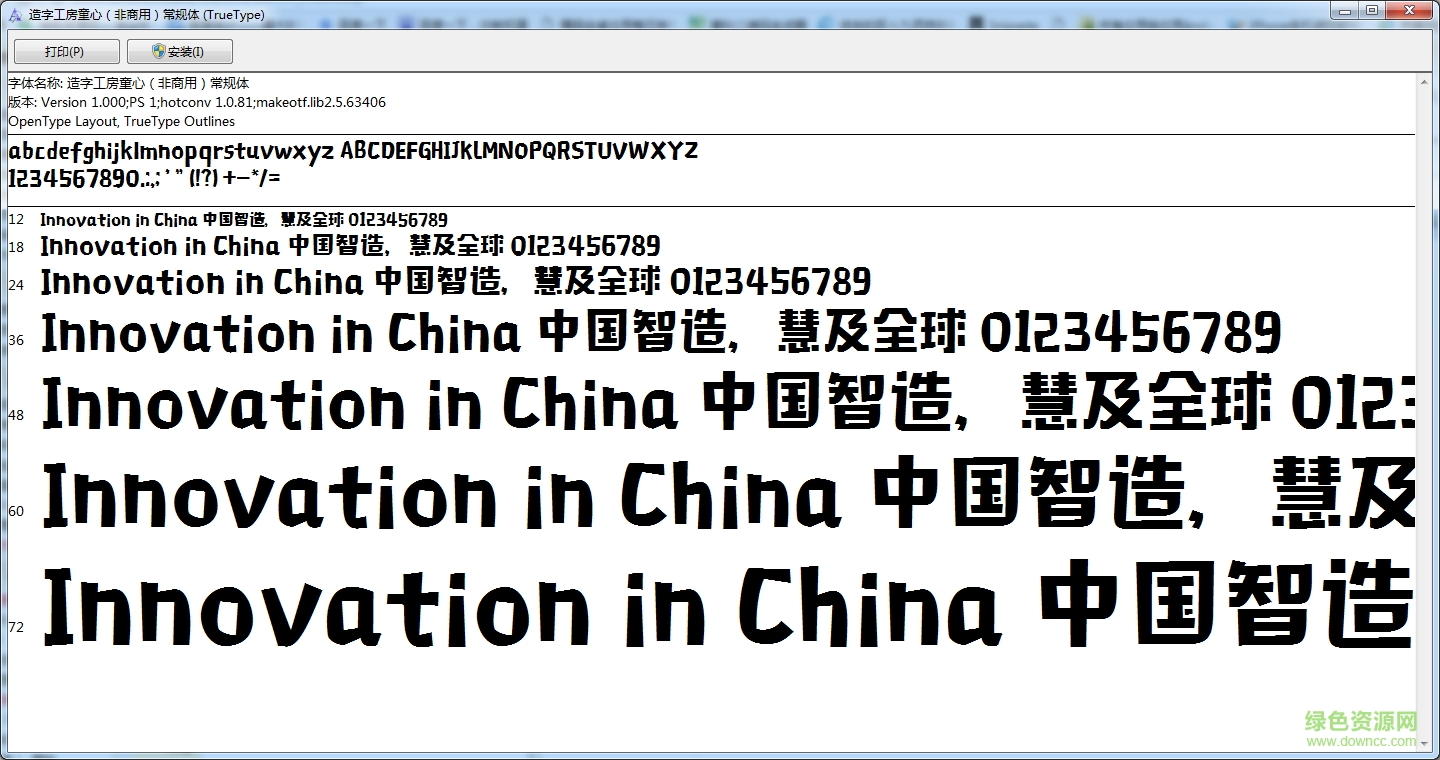
mftongxinnonco字體是一款個(gè)性強(qiáng)烈的可愛(ài)字體,線(xiàn)條較粗,字形生動(dòng),可以用在多媒體、平面設(shè)計(jì)、廣告、游戲、影視等各個(gè)領(lǐng)域,喜歡這款字體的小伙伴快來(lái)綠色資源網(wǎng)下載吧!
造字工房童心體,童趣盎然,字形有著濃郁詼諧可愛(ài)的氣息、其筆畫(huà)的穿插生動(dòng)、粗細(xì)形態(tài)肆意多變、欹正呼應(yīng)、給人活潑而不失穩(wěn)重之感,大氣而靈動(dòng)??诤推驳膱A潤(rùn)處理讓字形更加個(gè)性鮮明,生動(dòng)有趣,有著很強(qiáng)的視覺(jué)表現(xiàn)力。